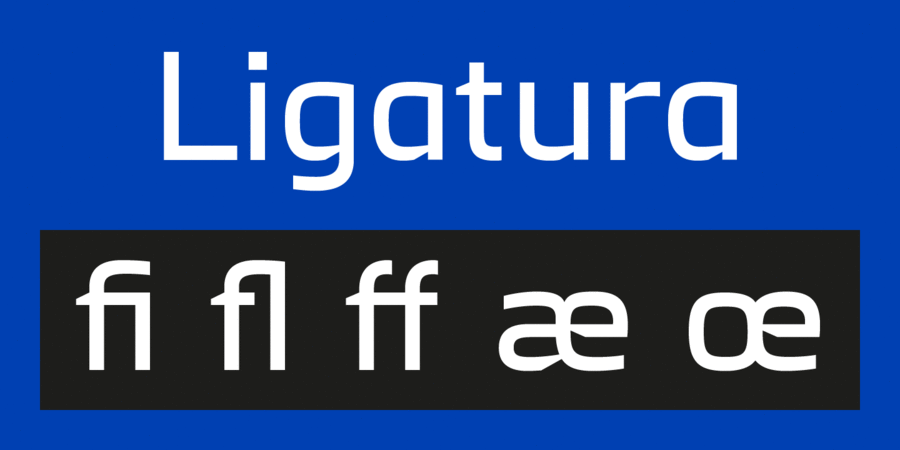
Rothko – міцний, статичний ґротеск. Округлі форми тяжіють до квадрату. Плавний силует літер контрастує з чітким ритмом складання. Яскравим акцентом виступають місця з'єднання діагональних штрихів. Шрифт містить стандартний набір латинки та кирилиці, математичні символи, стандартні лігатури, а також лігатуру для української пари «її». Rothko призначений для плакатних слоганів і яскравих заголовків. Шрифт розробив Олексій Поповцев у 2018 році.
лаконічний, космічний, техногенний, футуристичний, інженерний, креслярський, точний, рівний, переконливий, прямокутний, стабільний, твердий, серйозний, надійний, впевнений, сильний, стійкий, індустріальний, статичний, практичний, прагматичний, технічний, урбаністичний, грубий, якісний, міцний, логічний, міський, сучасний, гладенький, машинний, залізний, сталевий, різкий, чіткий, кінематографічний